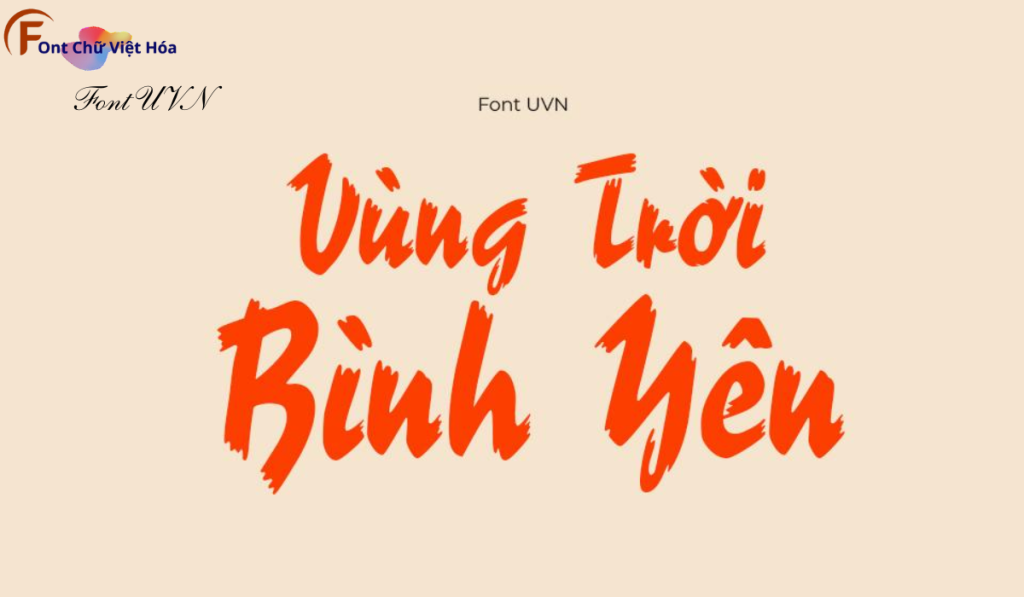
Font UVN Bút Lông 2 Việt Hóa
Tác giả: UVN Bút Lông 2 Việt Hóa
Bộ Font: UVN
Kiểu chữ: Viết tay
Độ dày: Mỏng, Vừa, Đậm
Font UVN Bút Lông 2 Việt Hóa là một font chữ viết tay cá tính, thuộc bộ font UVN. Được thiết kế với mục tiêu mang lại sự mềm mại và thanh thoát, font này lý tưởng cho các dự án thiết kế như thiệp mời, logo, và bao bì sản phẩm. Với các nét chữ uyển chuyển và độ dày đều đặn, Font UVN Bút Lông 2 Việt Hóa không chỉ dễ đọc mà còn tạo cảm giác thân thiện và gần gũi.